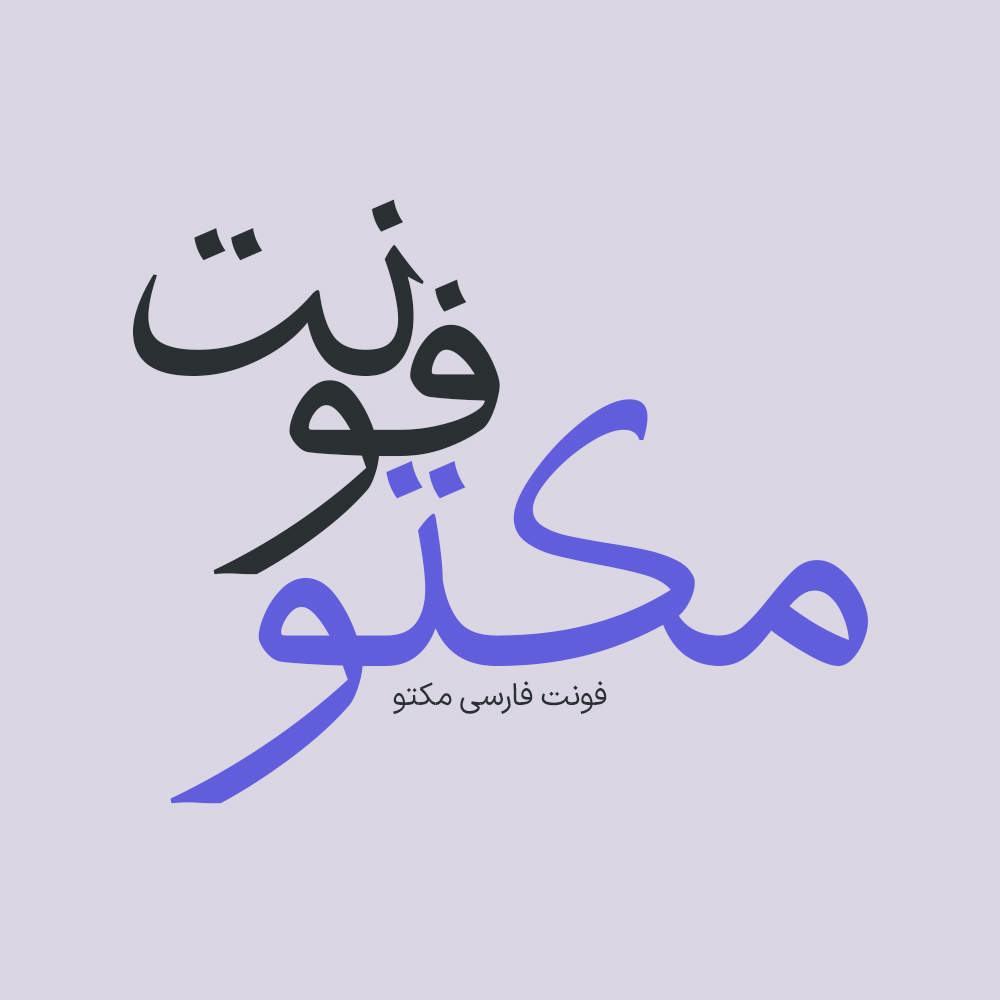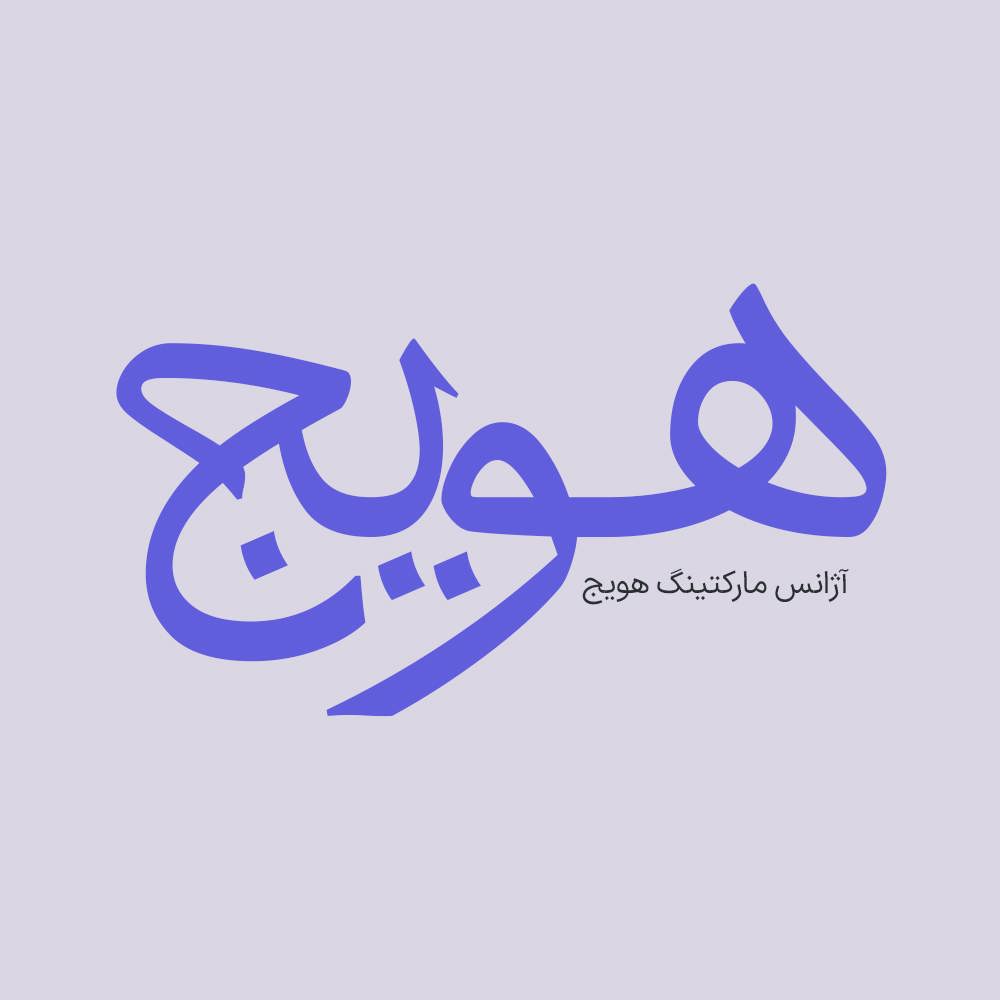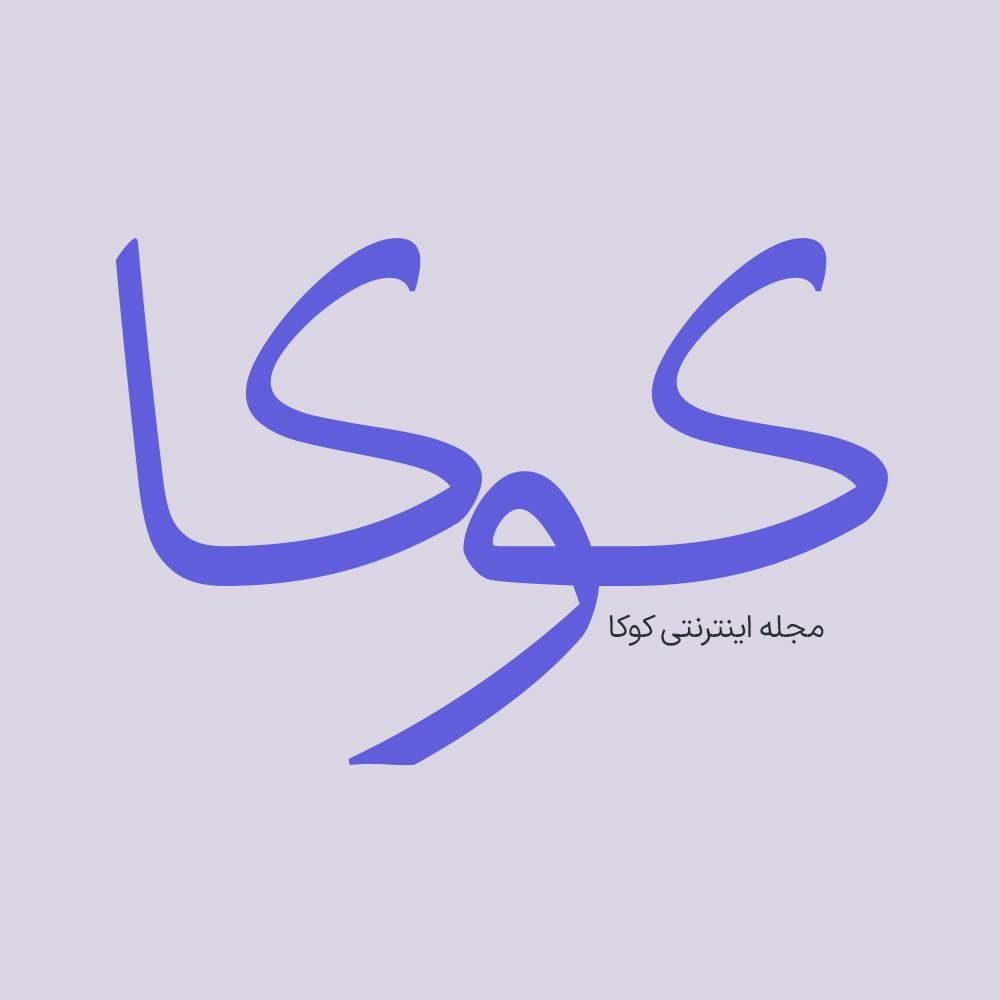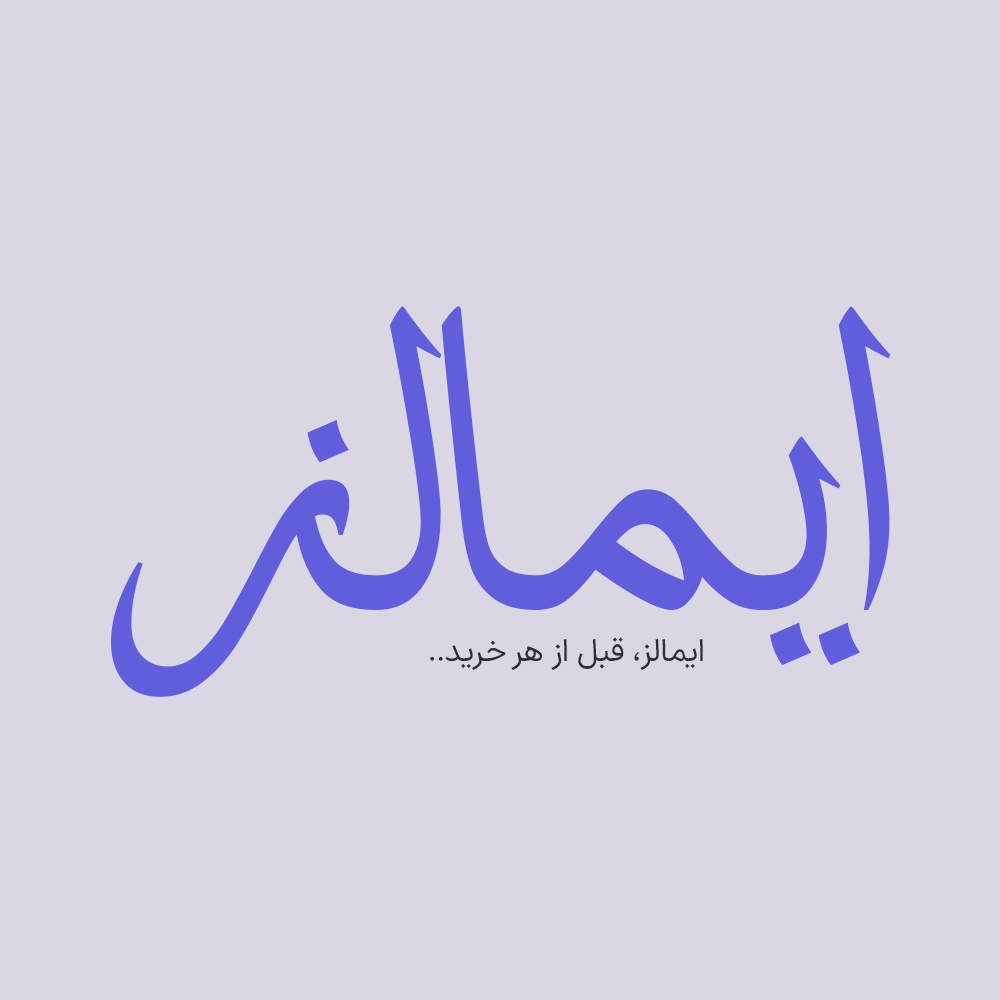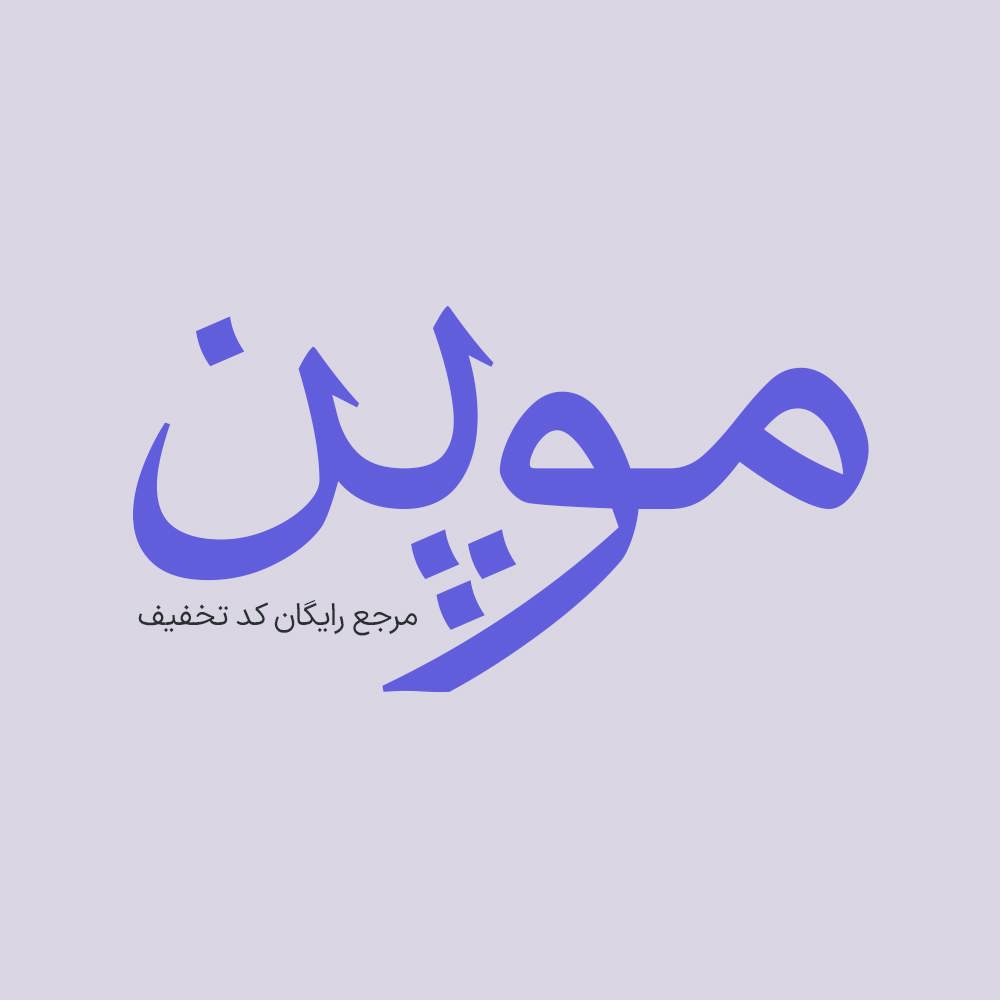
فونت فارسی مکتو Maktou Font
فونت فارسی مَکتو با دقت فنی بالا، طراحی زیبا، و کیفیت بی‌نظیری طراحی و منتشر شده است. فونت مَکتو به عنوان ابزار برجسته شما را در…
فونت فارسی مَکتو با دقت فنی بالا، طراحی زیبا، و کیفیت بی‌نظیری طراحی و منتشر شده است. فونت مَکتو به عنوان ابزار برجسته شما را در ارتقاء حرفه‌ای نمایش محتوای فارسی در وب و چاپ کمک خواهد کرد، فونت فارسی مَکتو در دسته فونت‌های نسخ نمایشی قرار دارد که برای طراحی‌های خلاق و متن‌های کوتاه بسیار مناسب است.
• مناسب طراحی بسته بندی ها و چاپ
• فونت ویژه تبلیغات محیطی
• فونت طراحی کاور اینستاگرام
• فونت حرفه ای برای تولید محتوا
• فونت فارسی طراحی وبسایت
• فونت طراحی لوگو تایپ فارسی
• مناسب استفاده در تابلو های چلنیوم و طراحی حروف